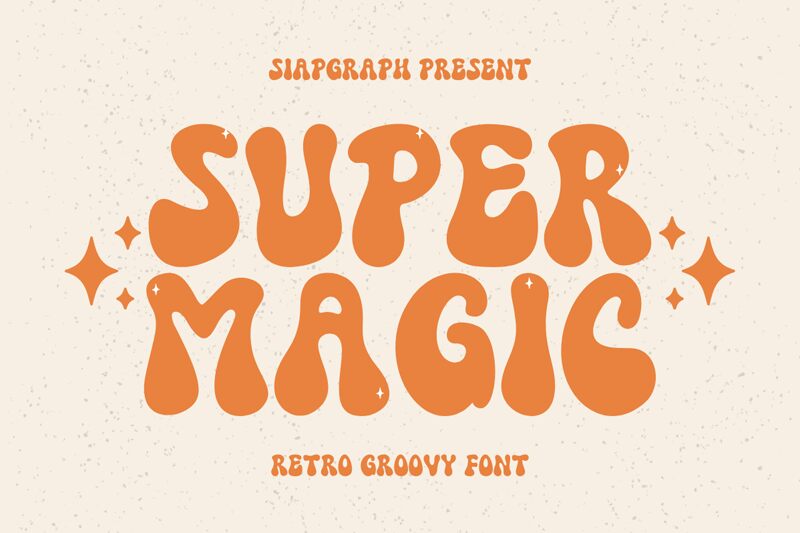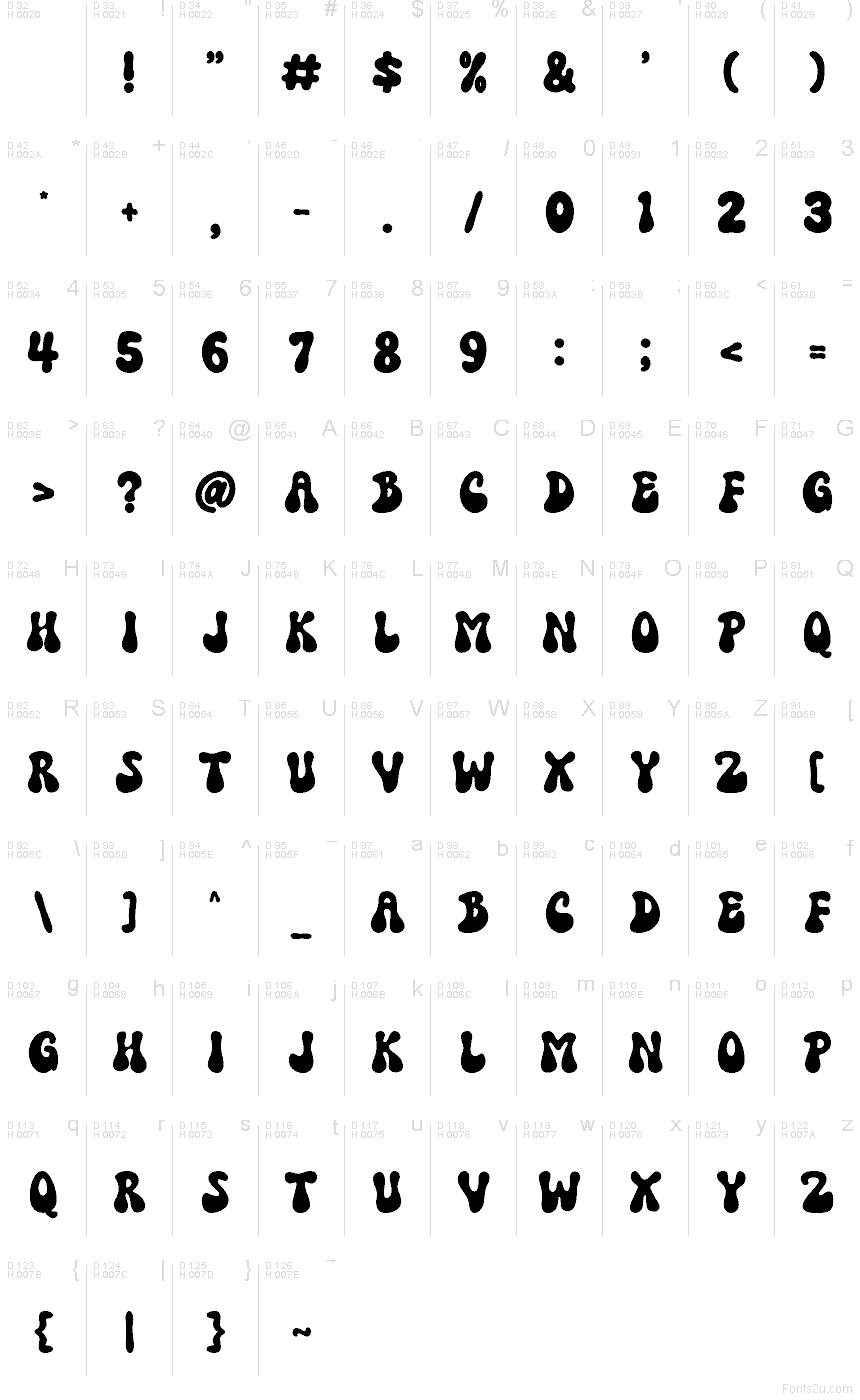
Super Magic Regular
Super Magic od SiapGraph Studio to darmowy font display w stylu groovy, ukształtowany przez pełne, miękkie linie i głębokie krzywizny, które nadają literom ciepły, dynamiczny i niemal roztopiony charakter. Ta płynna sylwetka nadaje projektom wyraźny, psychodeliczny klimat lat 70., unikając przy tym wrażenia kiczowatej ciekawostki.
Sprawdzi się idealnie przy oprawie płyt, plakatach festiwalowych, retro brandingu kawiarni, projektach naklejek czy tytułach w social mediach – wszędzie tam, gdzie potrzebujesz zaokrąglonego nagłówka, który przyjaźnie wypełnia przestrzeń. Szerokie, płynne formy nadają także opakowaniom czy grafikom eventowym ciepłą, niepowtarzalną obecność, przy której ostrzejsze kroje mogłyby wydać się zbyt sztywne.